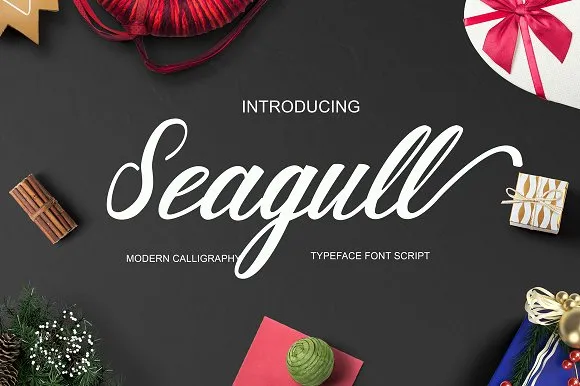
Seagull Script Font – Download Grátis
A Seagull é uma fonte criada a partir do estilo moderno do handlettering, ou seja, escrita à mão com influências de letras góticas contemporâneas e chamadas. Esta fonte foi desenhada diretamente à mão, capturando formas únicas e levemente surrealistas da calligrafia, mantendo a textura natural das linhas da escrita humana. Ideal para projetos que valorizam uma aparição fluida e versátil, a Seagull é perfeita para criar mensagens de impacto visual em variados ambientes digitais. Sujeitável tanto à elaboração quanto ao uso simples, ela combina perfeitamente com texturas serifadas e sem serifas, criando um equilíbrio entre modernidade e naturalidade. Uma fonte perfeita para quem busca um contraponto elegante no design de letras digitais.